Font islami merujuk pada jenis font yang didesain khusus dengan unsur-unsur islami, seperti kaligrafi Arab, ayat Al-Qur’an, dan motif-motif tradisional. Tren penggunaan font Islami semakin berkembang di kalangan desainer. Desain-desain yang menggabungkan elemen-elemen Islami memberikan sentuhan artistik dan spiritual yang unik.
Contohnya, dalam desain grafis cetak, font Islami sering digunakan dalam pembuatan poster, cover buku, kartu ucapan, dan lain-lain. Sedangkan, dalam desain grafis digital, font Islami sering ditemukan dalam pembuatan situs web dan aplikasi islami, konten media sosial, dan lain-lain. Nah, apabila Anda sedang mencari font Islami, dalam artikel ini, kami menyediakan 40 pilihan font islami keren dan gratis yang siap untuk Anda gunakan dalam berbagai proyek desain Anda. Yuk, simak daftarnya di bawah ini!
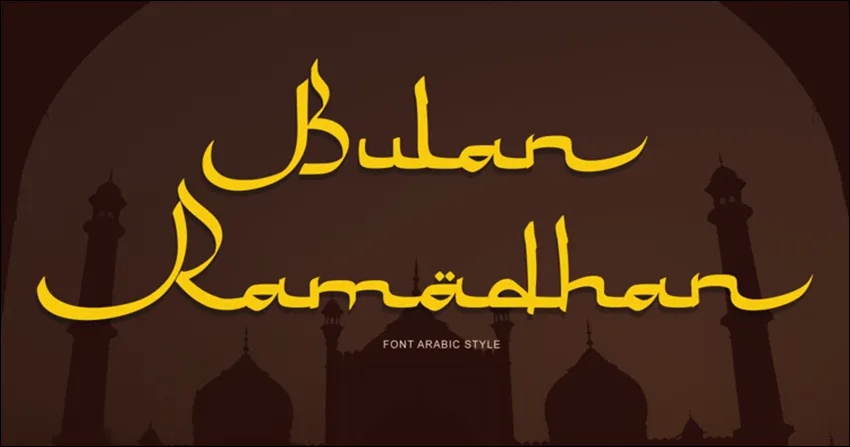
Font pertama adalah Bulan Ramadhan. Sebagaimana namanya, font islami ini cocok digunakan untuk merayakan bulan suci Ramadhan dengan desain font nya yang elegan.
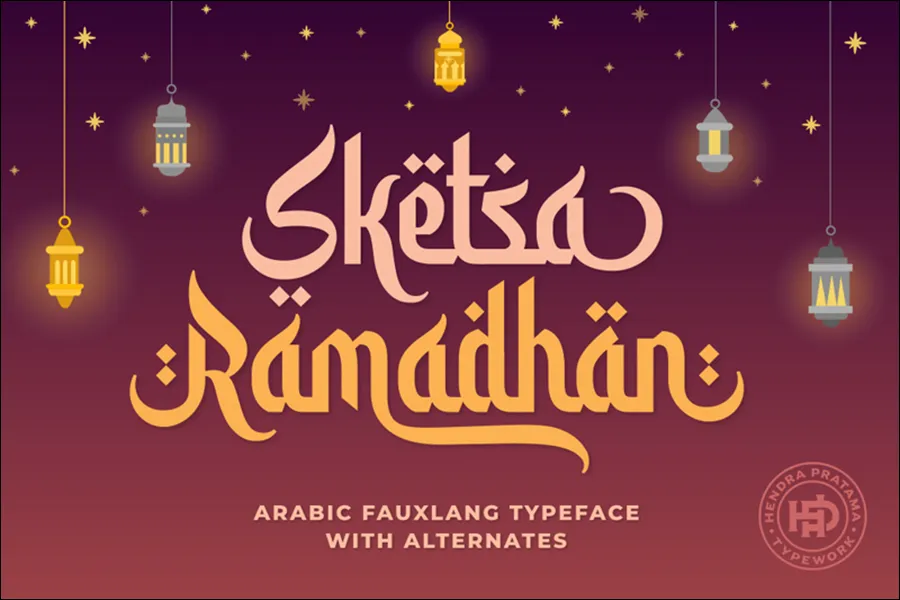
Font kedua adalah Sketsa Ramadhan. Dengan desainnya yang unik seperti sketsa, font ini dapat memberikan sentuhan kreatif pada desain-desain yang berkaitan dengan bulan Ramadhan, seperti poster atau kartu ucapan.
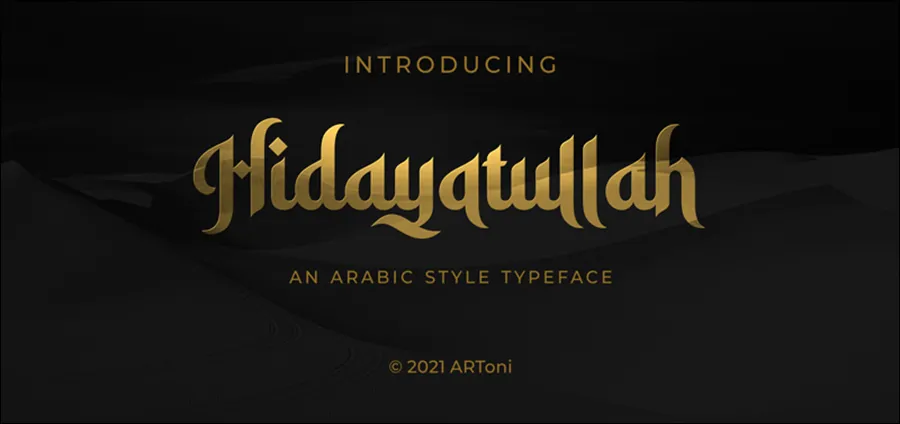
Selanjutnya adalah Hidayatullah. Font ini memiliki keanggunan dalam desainnya, cocok digunakan untuk menyampaikan pesan-pesan keagamaan atau nasihat-nasihat Islami dalam desain-desain grafis.
Font ini memiliki desain kaligrafi dengan nuansa yang lembut dan feminin, cocok digunakan untuk desain-desain yang bertema kebaikan, kedamaian, atau kesejahteraan, sesuai dengan makna nama font tersebut.
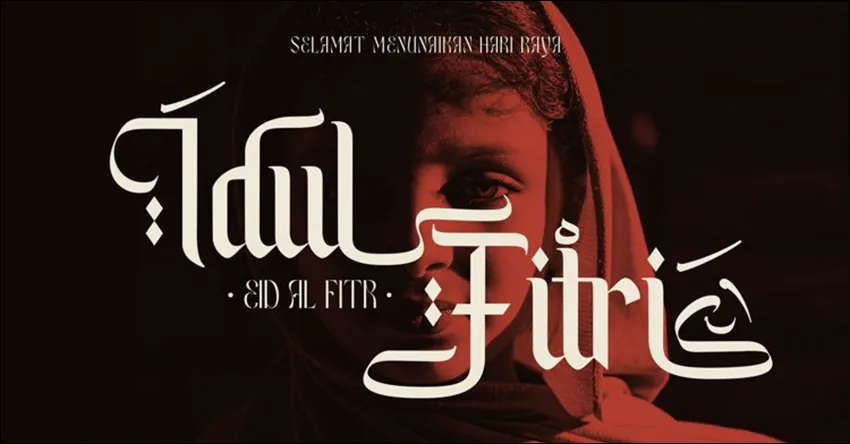
Dengan bentuk huruf yang khas, font ini cocok untuk digunakan dalam desain-desain yang membutuhkan kesan tradisional atau klasik, serta dapat memberikan sentuhan Islami yang kuat, seperti pada desain-desain hari raya, dan lain-lain.
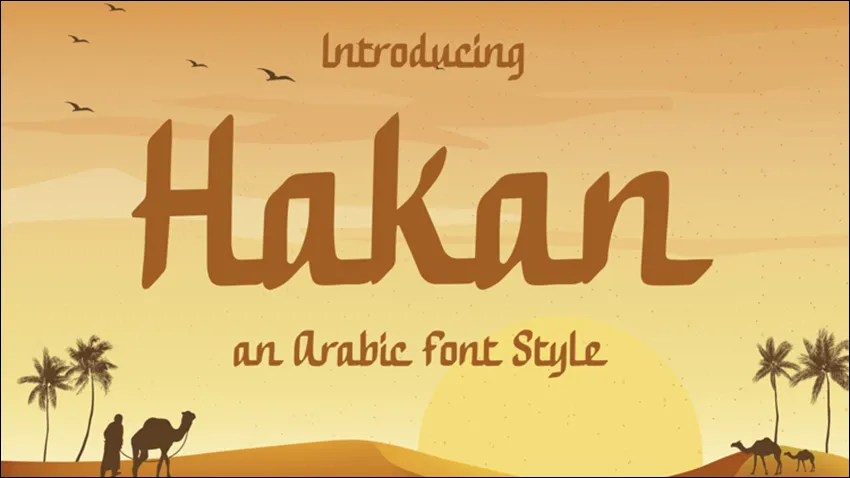
Hakan memiliki desain font yang sederhana namun tetap terlihat modern, cocok digunakan untuk berbagai desain grafis baik yang bersifat formal maupun informal.
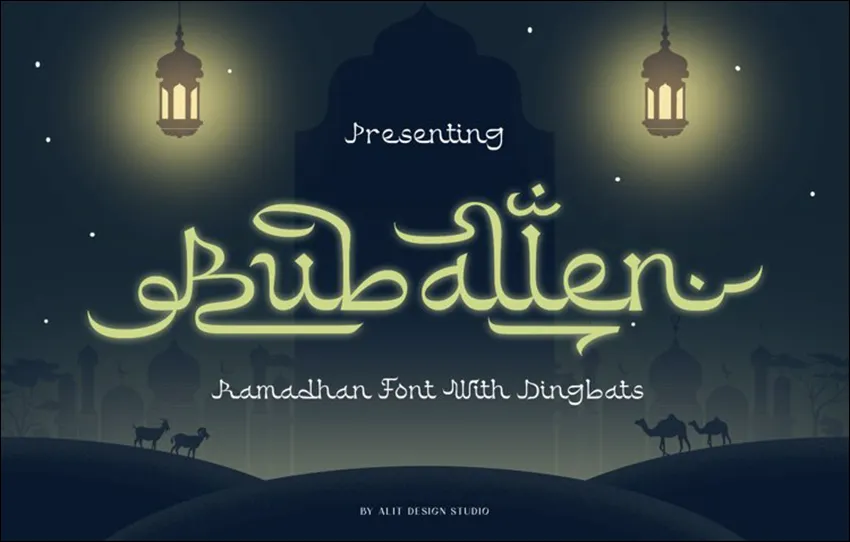
Dengan gaya huruf yang khas, font ini cocok digunakan untuk menambahkan nuansa keceriaan dan kreativitas pada desain-desain yang berkaitan dengan tema Islami, seperti bulan Ramadhan, Idul Fitri, dan lain-lain.
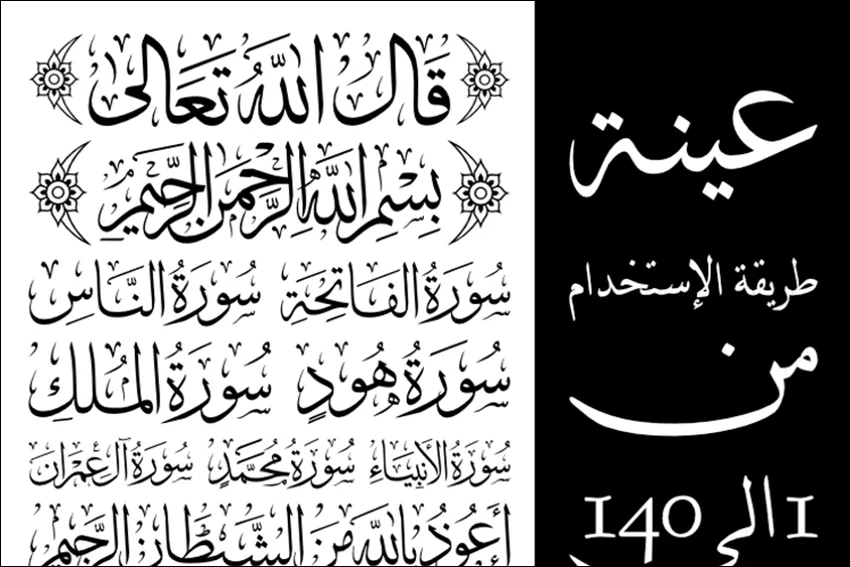
Arab Quran Islamic 140 didesain khusus dengan gaya khat yang menyerupai tulisan Arab dalam Al-Quran, cocok digunakan untuk desain-desain yang berkaitan dengan teks-teks agama Islam.
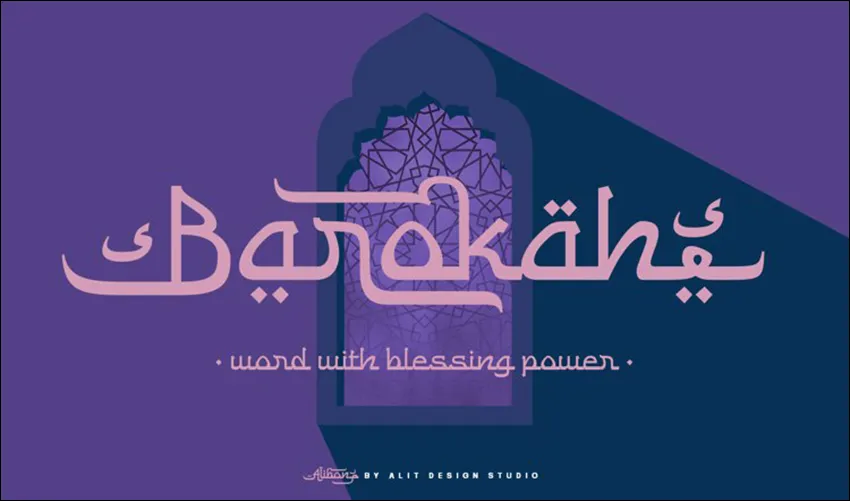
Dengan desain kaligrafi yang elegan, font ini cocok digunakan untuk berbagai desain grafis termasuk yang bertema Islami seperti kartu ucapan atau poster.
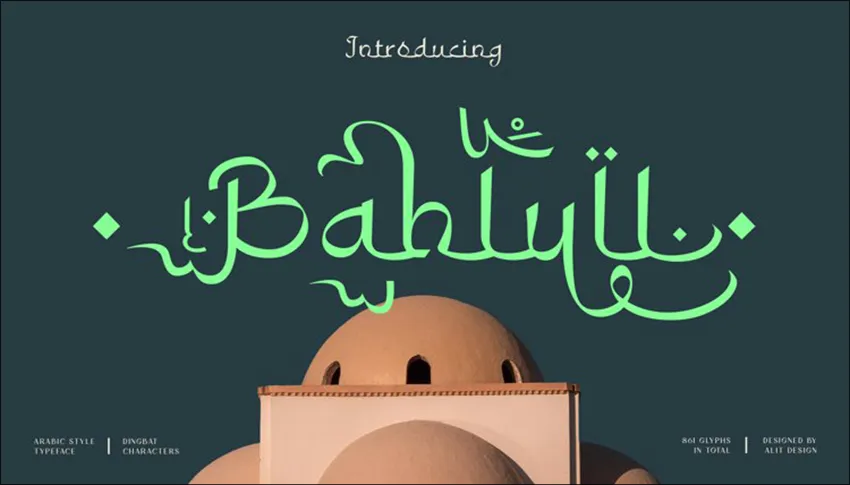
Font ini memiliki desain kaligrafi yang aesthetic dan menarik perhatian, cocok digunakan untuk desain-desain yang ingin menyampaikan nilai-nilai agama Islam.
Dengan desain yang sederhana namun elegan, font ini cocok digunakan untuk desain-desain monogram yang ingin menonjolkan pesan-pesan Islami dengan kesederhanaan.
Font ini memiliki keindahan dalam desainnya yang seperti permata, cocok digunakan untuk desain-desain yang ingin menyoroti keindahan dan keistimewaan bulan Ramadhan.
Font slab-serif ini menampilkan desain bulat yang mengalir, cocok digunakan untuk desain-desain yang ingin menyambut atau mengundang dengan penuh kebaikan, sesuai dengan makna “Marhaban” yang berarti “selamat datang”.
Dengan nama yang menggambarkan keistimewaan bulan Ramadhan, font ini cocok digunakan untuk desain-desain yang ingin menekankan keagungan dan kemuliaan bulan tersebut.
Font ini cocok digunakan untuk menyampaikan salam atau pesan-pesan positif terkait bulan Ramadhan dalam desain-desain grafis seperti kartu ucapan atau banner.
Dengan desain vintage yang unik dan menarik, font ini cocok digunakan untuk desain-desain yang ingin menonjolkan kekreatifan dan keunikan dalam menyampaikan pesan-pesan Islami.
Font ini memiliki desain kaligrafi yang dekoratif. Cocok digunakan untuk desain-desain yang ingin menyoroti pesan-pesan Islami yang mendalam dan memikat hati.
Dengan desain kaligrafi yang lembut dan elegan, font ini cocok digunakan untuk desain-desain headline islami.
Font ini memiliki desain yang mewah dan tegas, cocok digunakan untuk desain-desain nama masjid, kaligrafi, dan lain-lain. yang ingin menyoroti kemewahan dan ketegasan.
Tidak, setiap font islami memiliki karakteristik dan kegunaannya sendiri. Misalnya, beberapa font cocok untuk desain cetak, sementara yang lain lebih sesuai untuk desain digital atau web. Penting untuk memilih font yang sesuai dengan konteks dan tujuan desain.